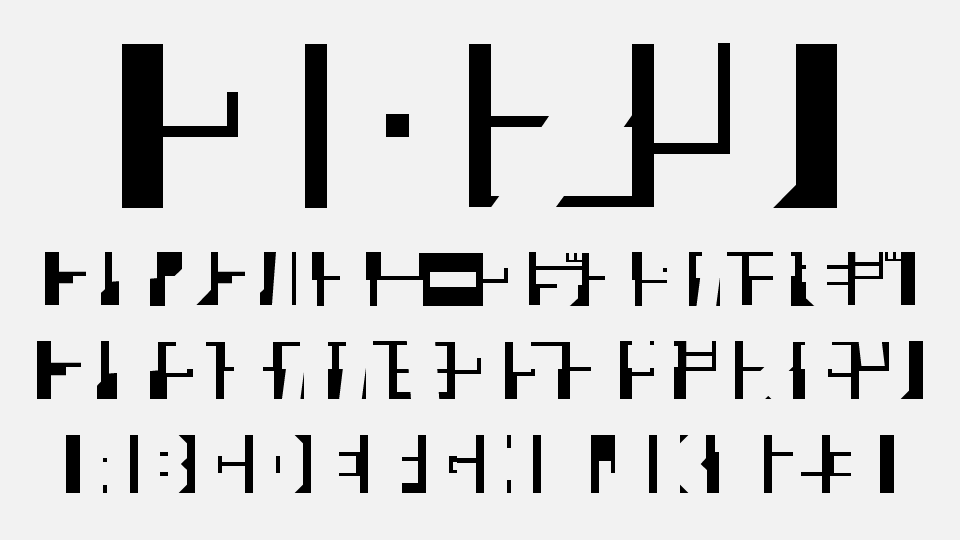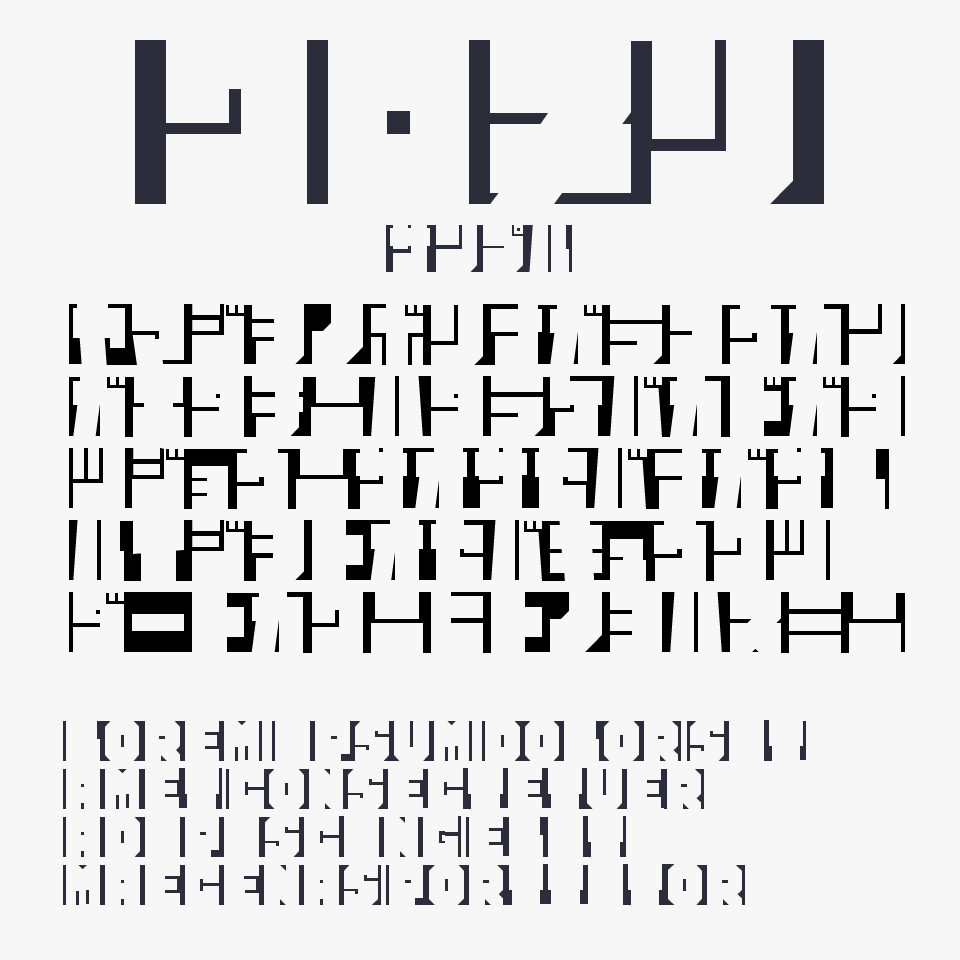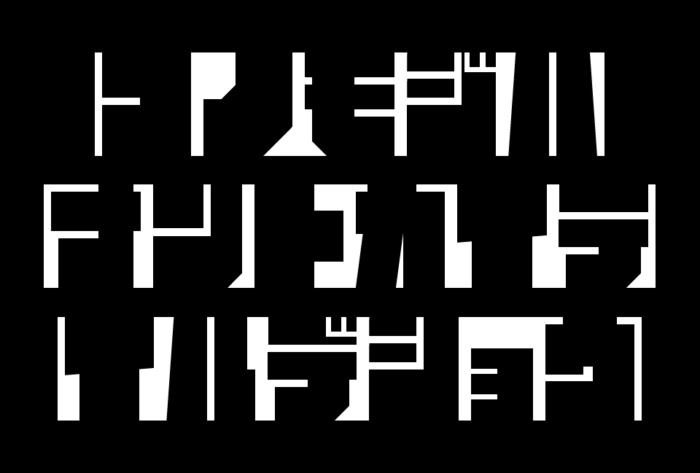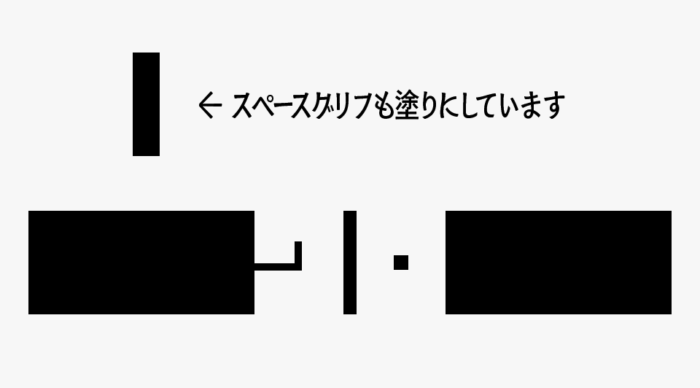
クロヌリフォント
クロヌリフォントは、読めなさそうで読める文字として制作されたカタカナフォントです。
黒い部分を読もうとする視覚的な習性を逆手に取ったネタフォントです。黒い部分は文字のように見えて実際には読めず、反対に「抜き」で表現された白い部分が文字として浮かび上がります。そのため、直感的には非常に読みにくいデザインにしており、見る人の感覚を少し混乱させるような独特のデザインになっています。
白黒反転してもなお読みづらい、不思議な仕掛けのフォントです。だけど、一度文字の形を理解してしまうと、不思議なことにもうそれ以外の形には見えなくなります。ネタフォントとしての要素が強いため、暗号文字やクイズ系のデザインなどに取り入れると、ユニークで面白い演出ができます。
スペースグリフも塗りにしているので、装飾的にお使いください。
収録文字は、カタカナ・アルファベット・数字・一部記号が収録されています。